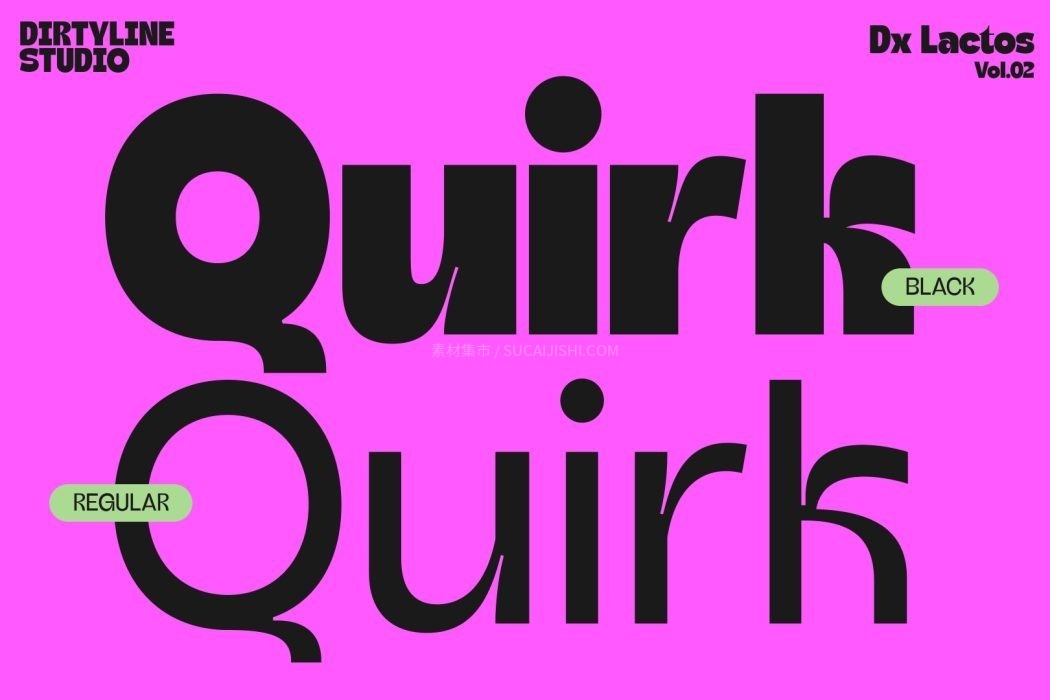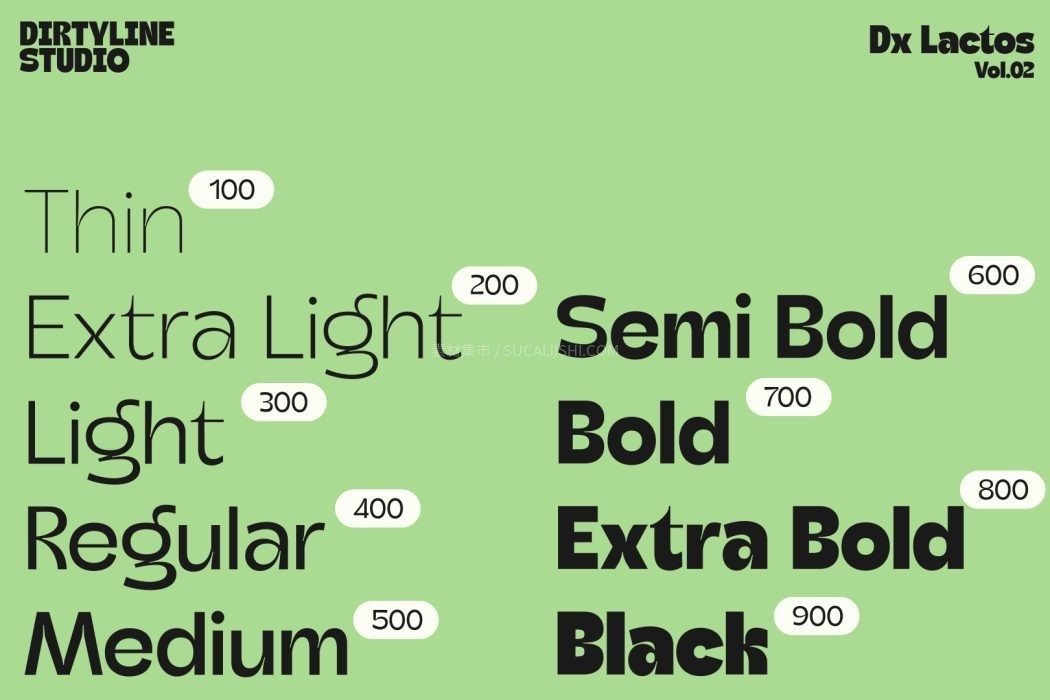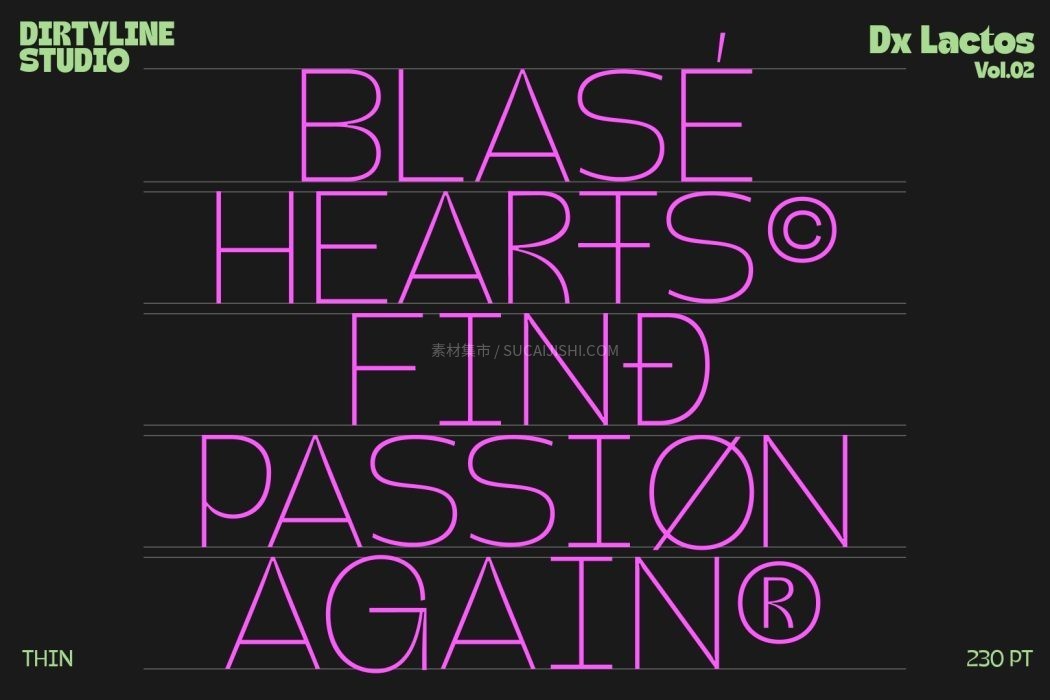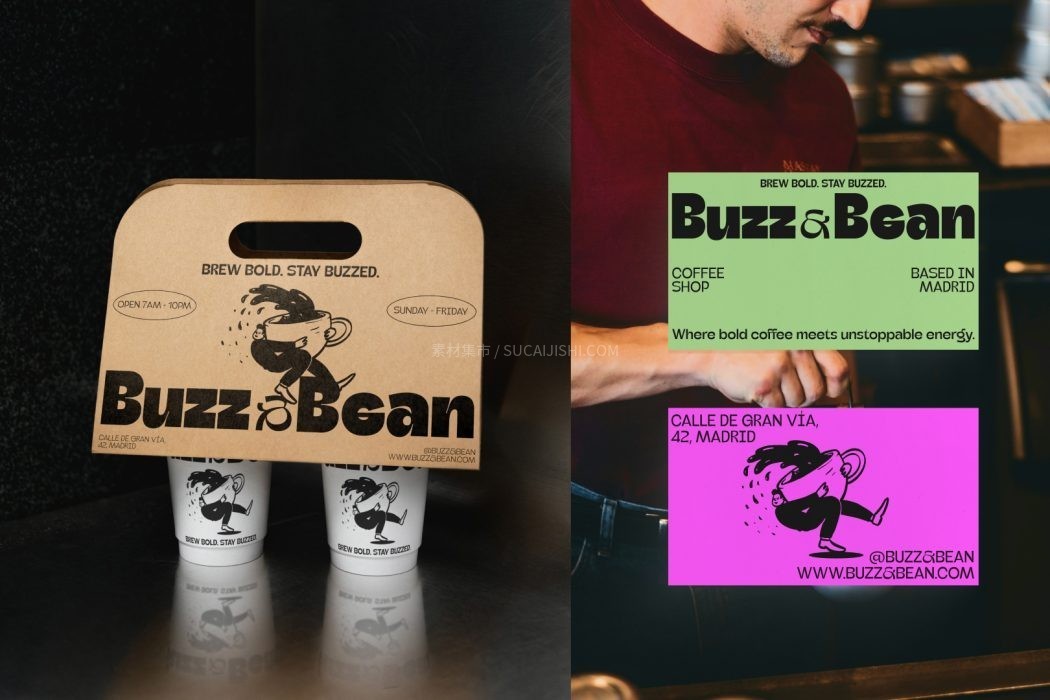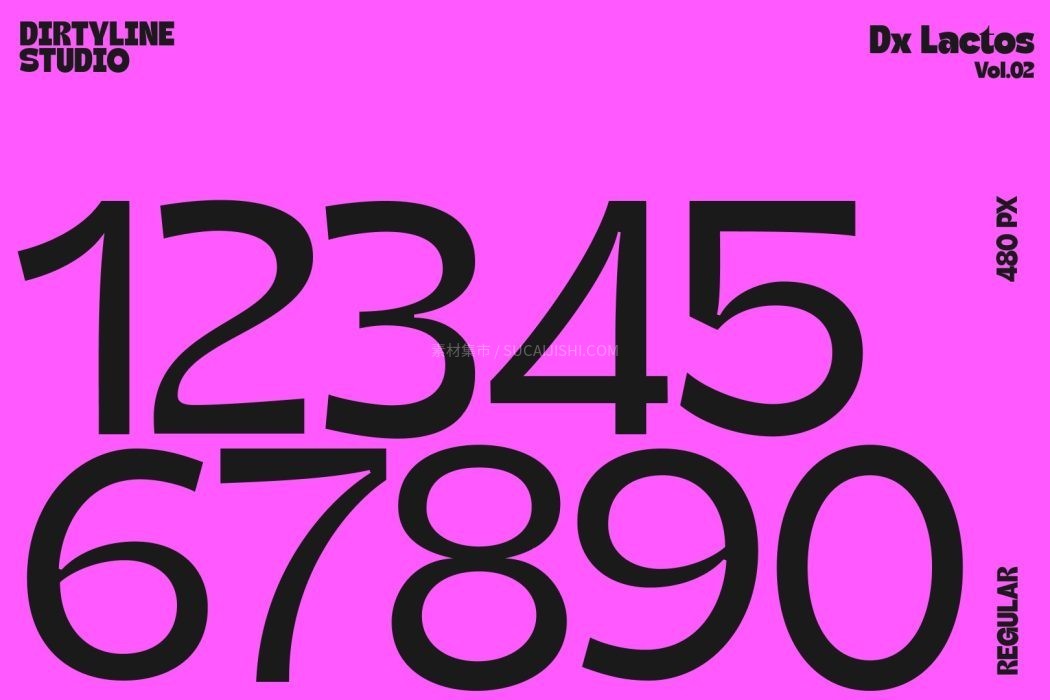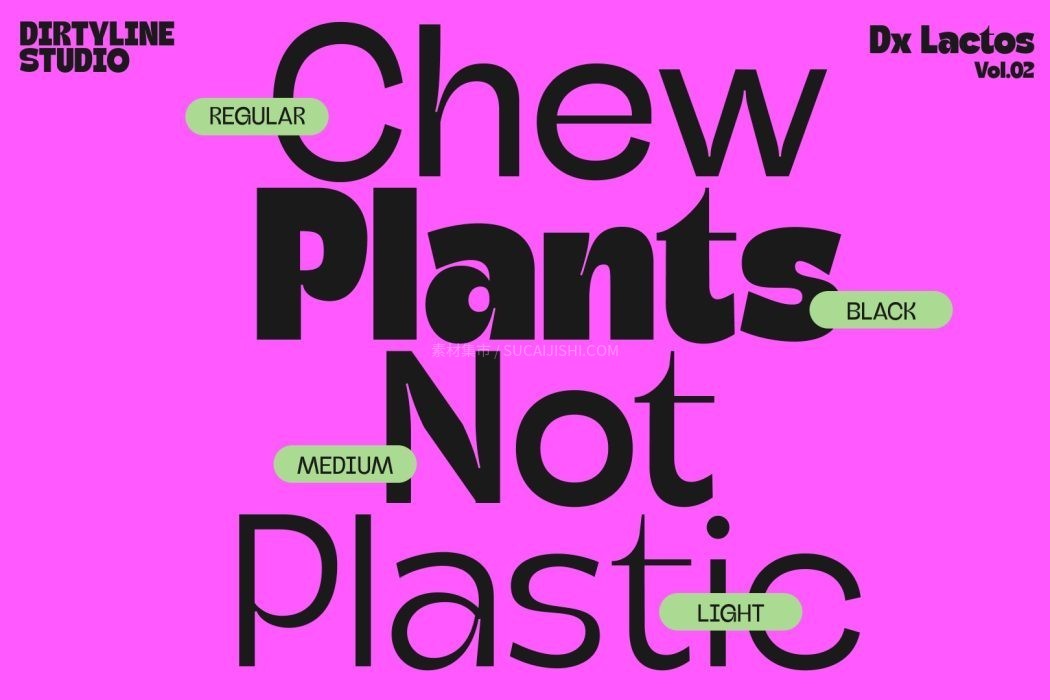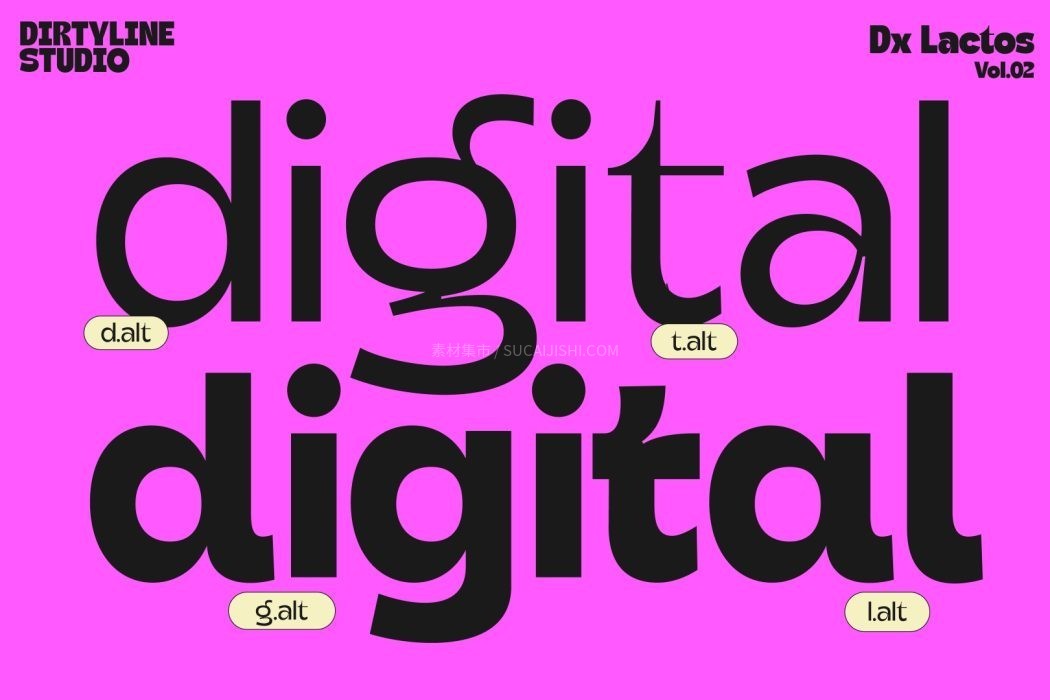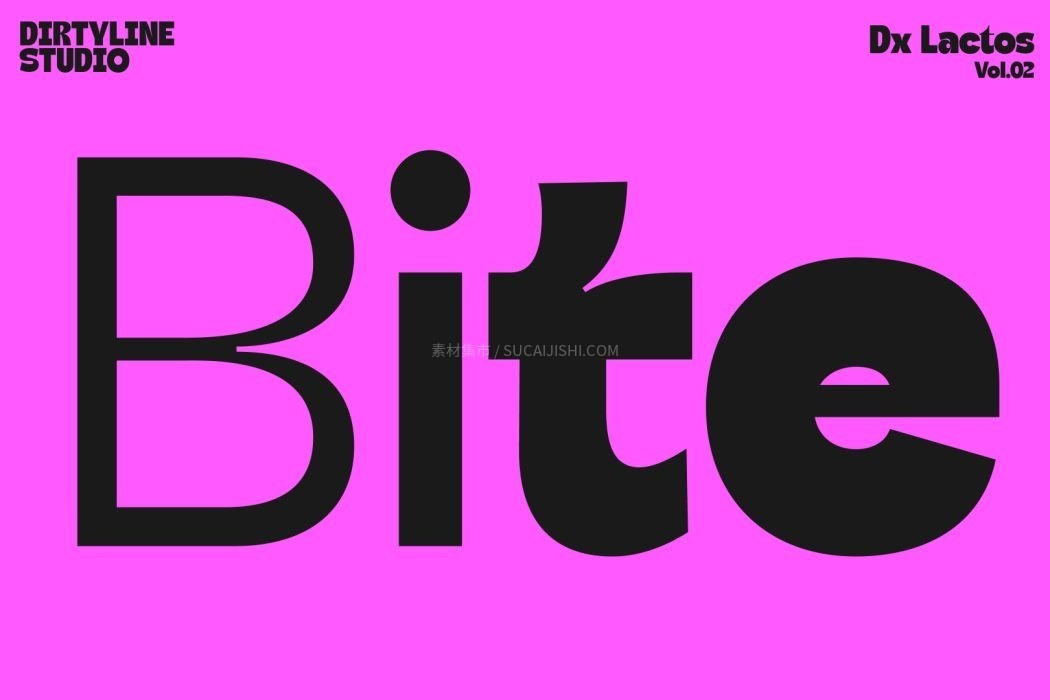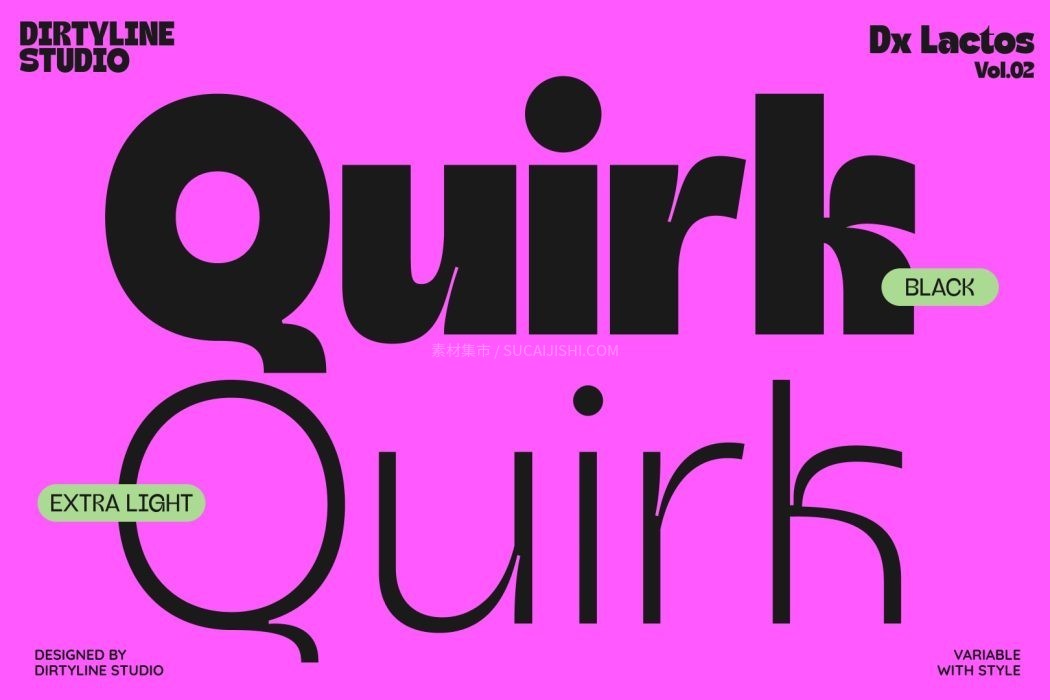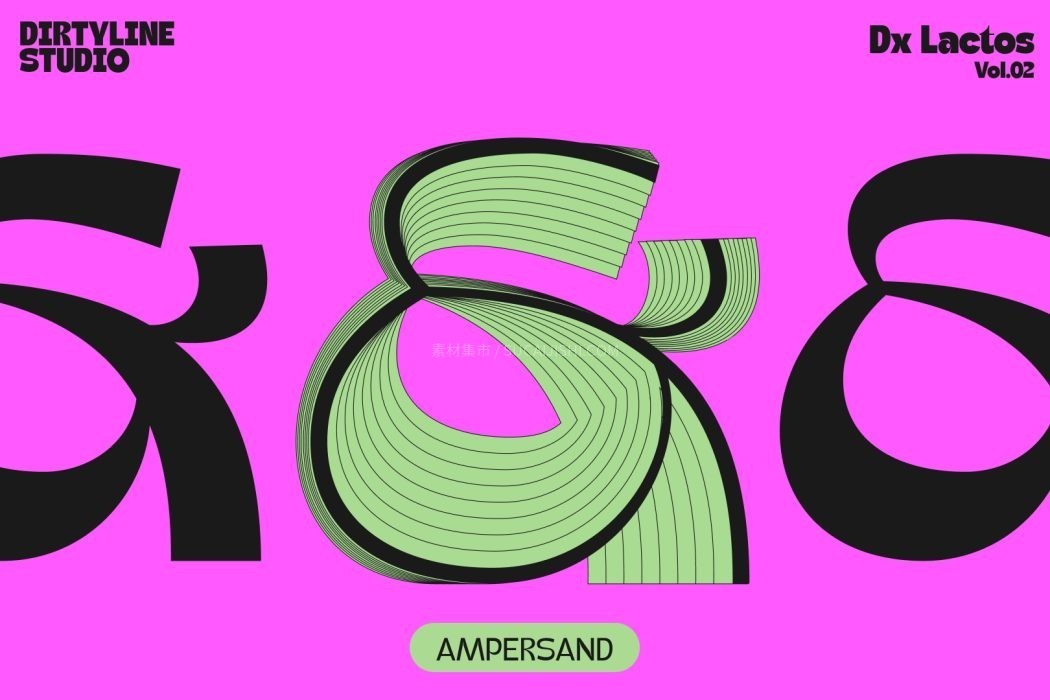
Dx Lactos 创意可变字体
想要让你的设计瞬间抓住眼球?这款自带“趣味光环”的 Dx Lactos 绝对是破局之选!它直接打破了传统字距与笔画的条条框框,用极为大胆的线条和灵活的可变字宽,释放出满满的个性张力。整套字库包含了完整的 9 个字重,作为一款原生可变字体,它简直是网页排版的“视觉放大器”——不管是拿来做极具冲击力的 H1、H2、H3 标题,还是用于影视剧宣发、主流娱乐平台的海报,都能让数字界面充满活力与互动感,让受众一眼惊艳,过目不忘。